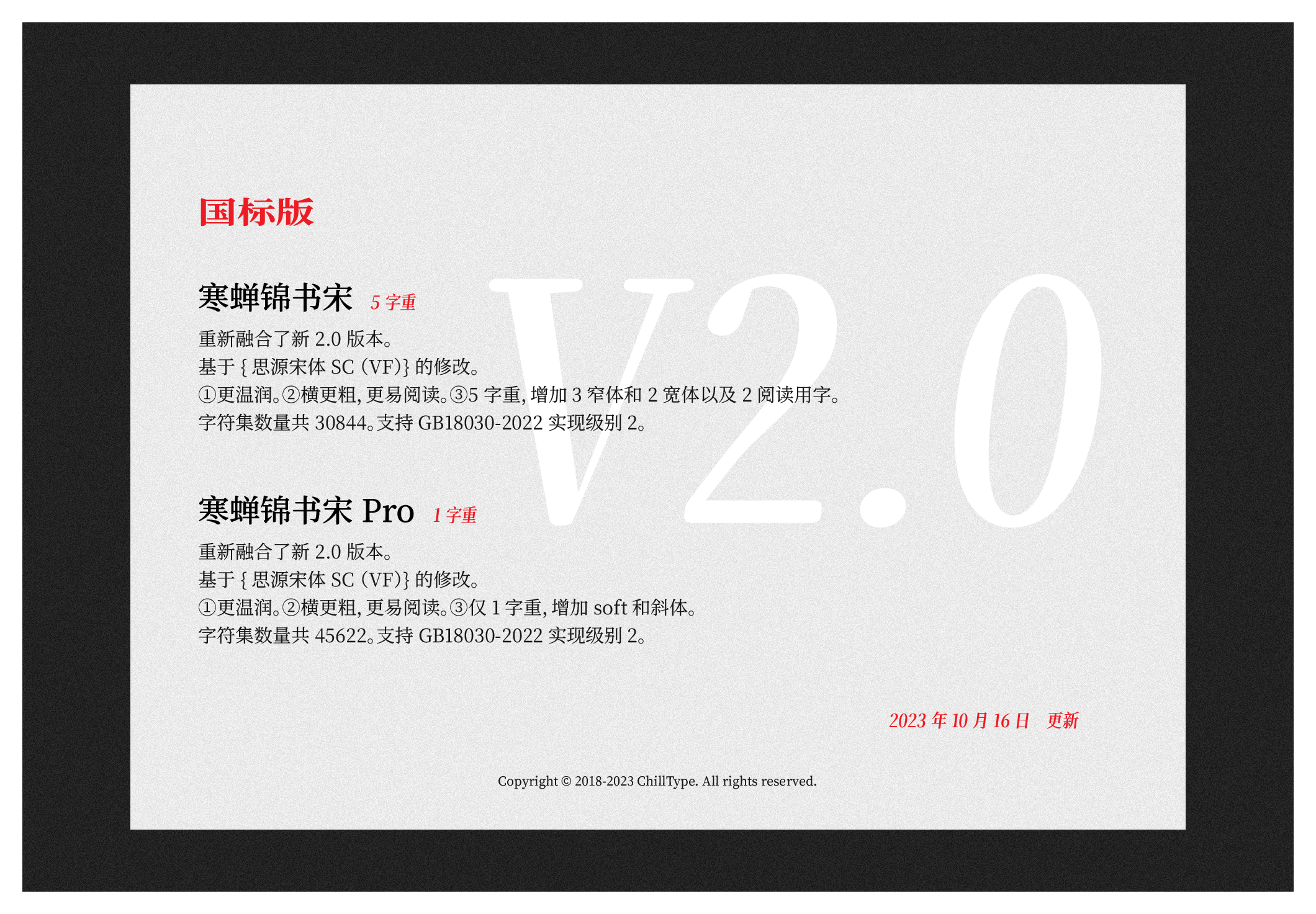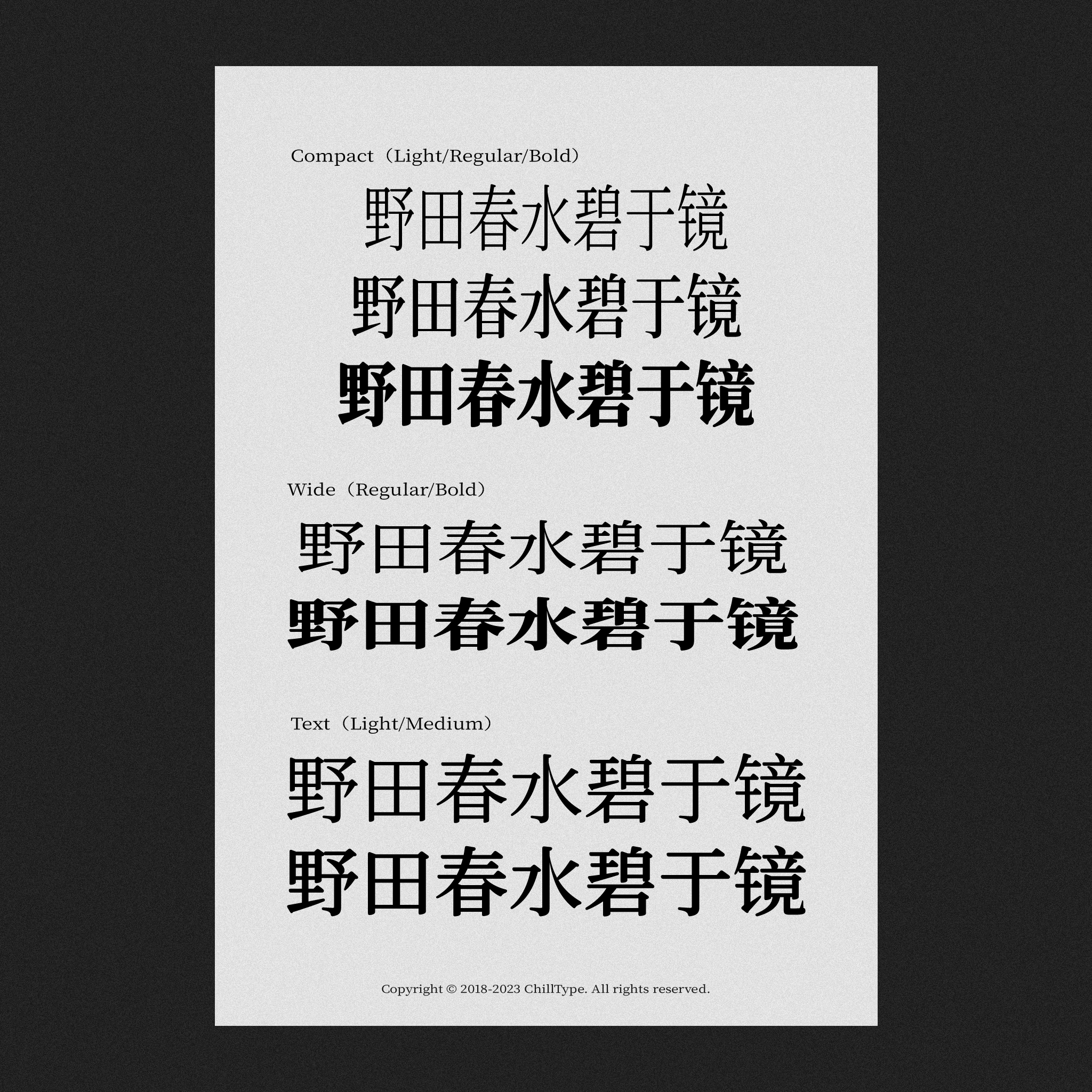
寒蝉锦书宋(ChillJinshuSong)是在优质中文字体思源宋体(Source Han Serif)基础上进行深度定制与修改而成的一款字体。它在保留思源宋体原有清晰骨架与结构美感的同时,进行了多方面的优化创新,使其呈现出更加温润、亲和的视觉特质。
最显著的特征之一是添加了细腻的圆角处理。无论是笔画的起笔、收笔,还是转折与勾点部分,原本较为锐利的边角都经过了圆滑过渡,使得整体字形避免了生硬感,转而流露出柔和、舒缓的视觉印象,阅读起来更为舒适悦目。
在排版细节上,锦书体进行了全面的重构与优化。设计师重新调整了字体的内白、中宫以及笔画部件之间的布白关系,使字距、行距的配合更为和谐。特别值得一提的是,它对原字体的字重比例进行了精密校准,使得从细体到粗体的各级字重在笔画粗细上过渡更加均匀、均衡,避免了过粗或过细带来的视觉跳跃,从而显著提升了长篇文本阅读的流畅性与舒适度。
这款字体被赋予了“锦书”之名,寓意丰富而美好。其一,“锦书”本身即指华美的书信、文章,喻指使用此字体能够为文本增添文采与美感,有“锦上添花”之意。其二,“锦”也象征着前程似锦、生活美好,寄托了通过精良的字体呈现,为读者和作者都带来愉快视觉享受与美好祝愿的期盼。因此,寒蝉锦书宋不仅是一款功能优化的阅读字体,更承载了将汉字之美与人文祝福相结合的设计理念。